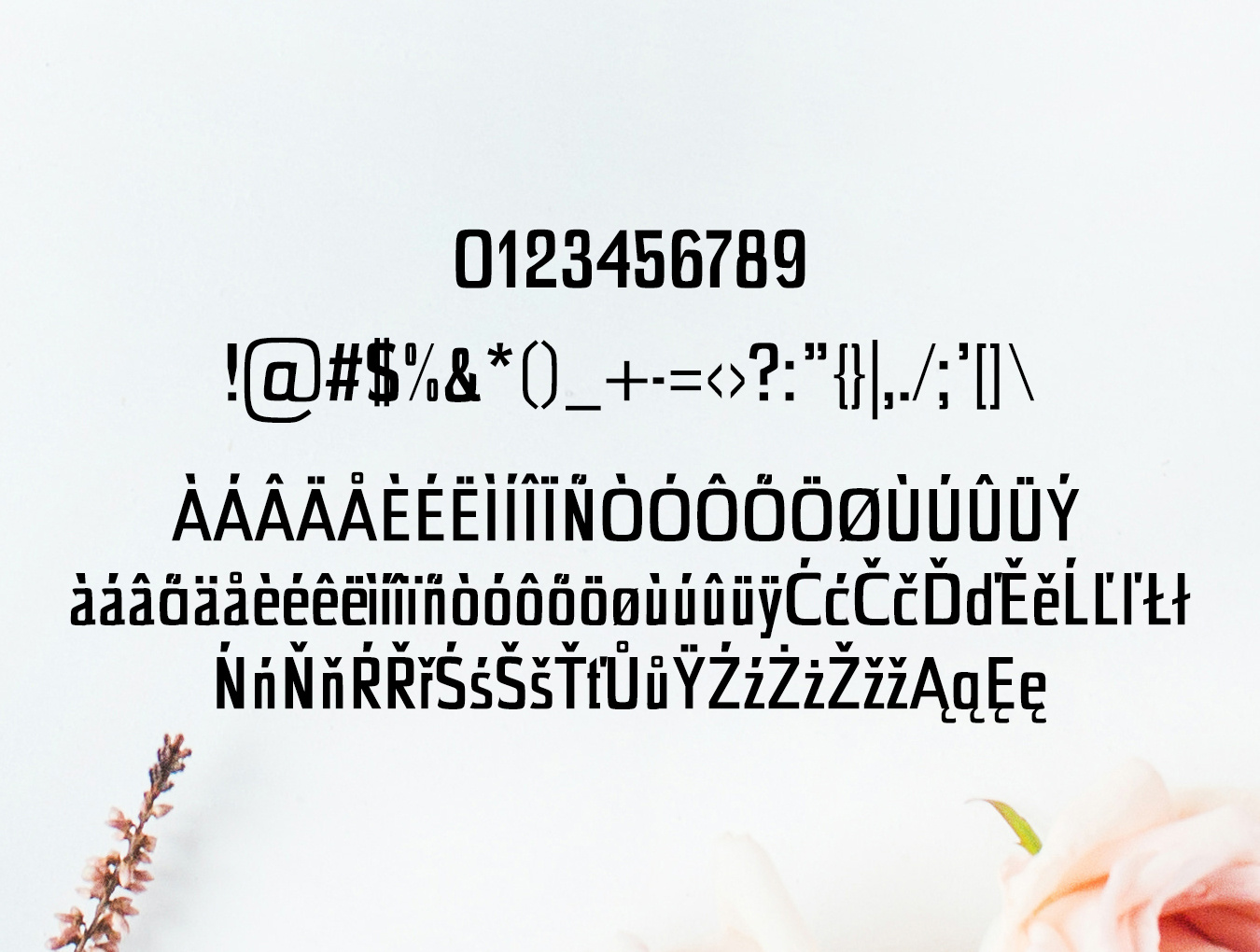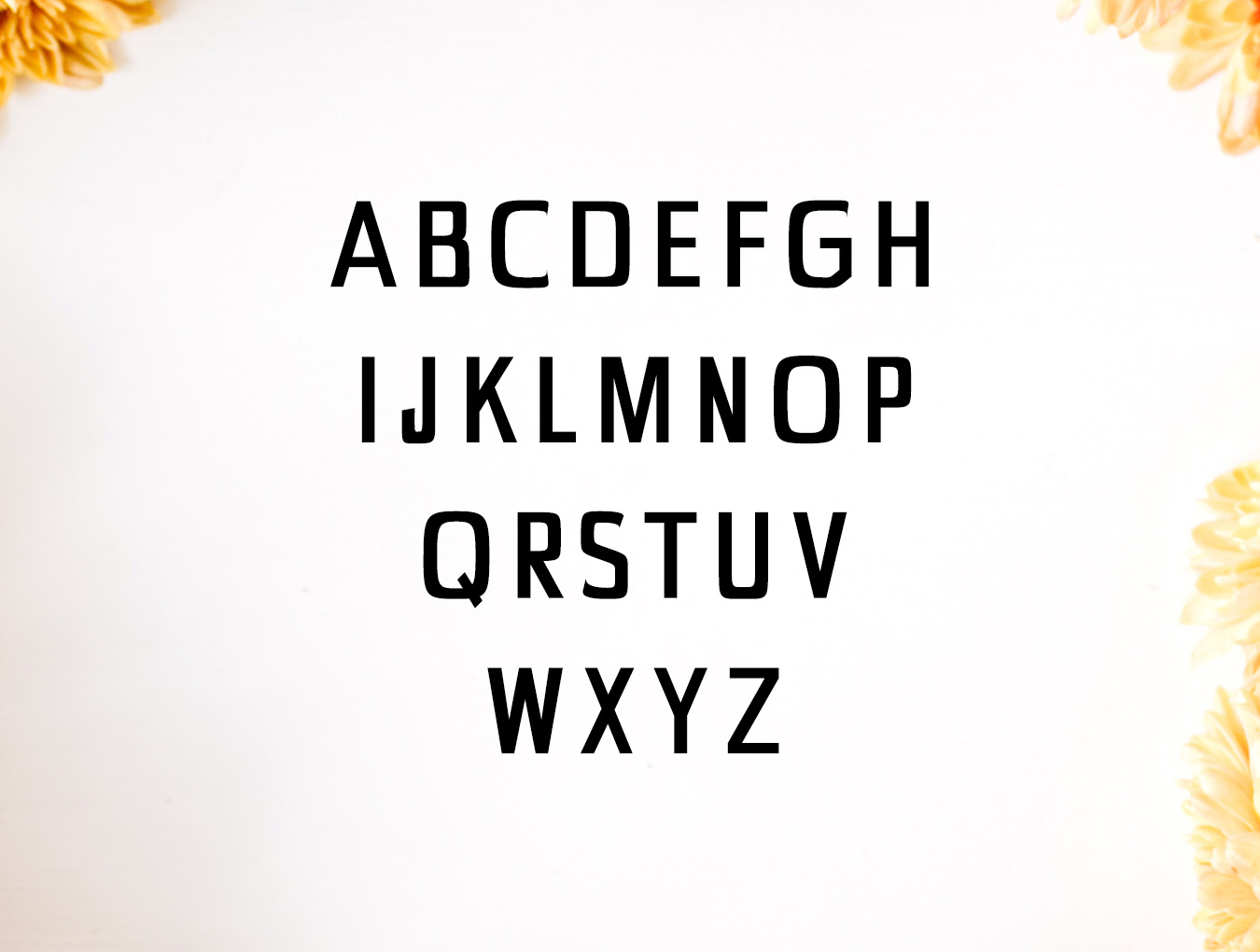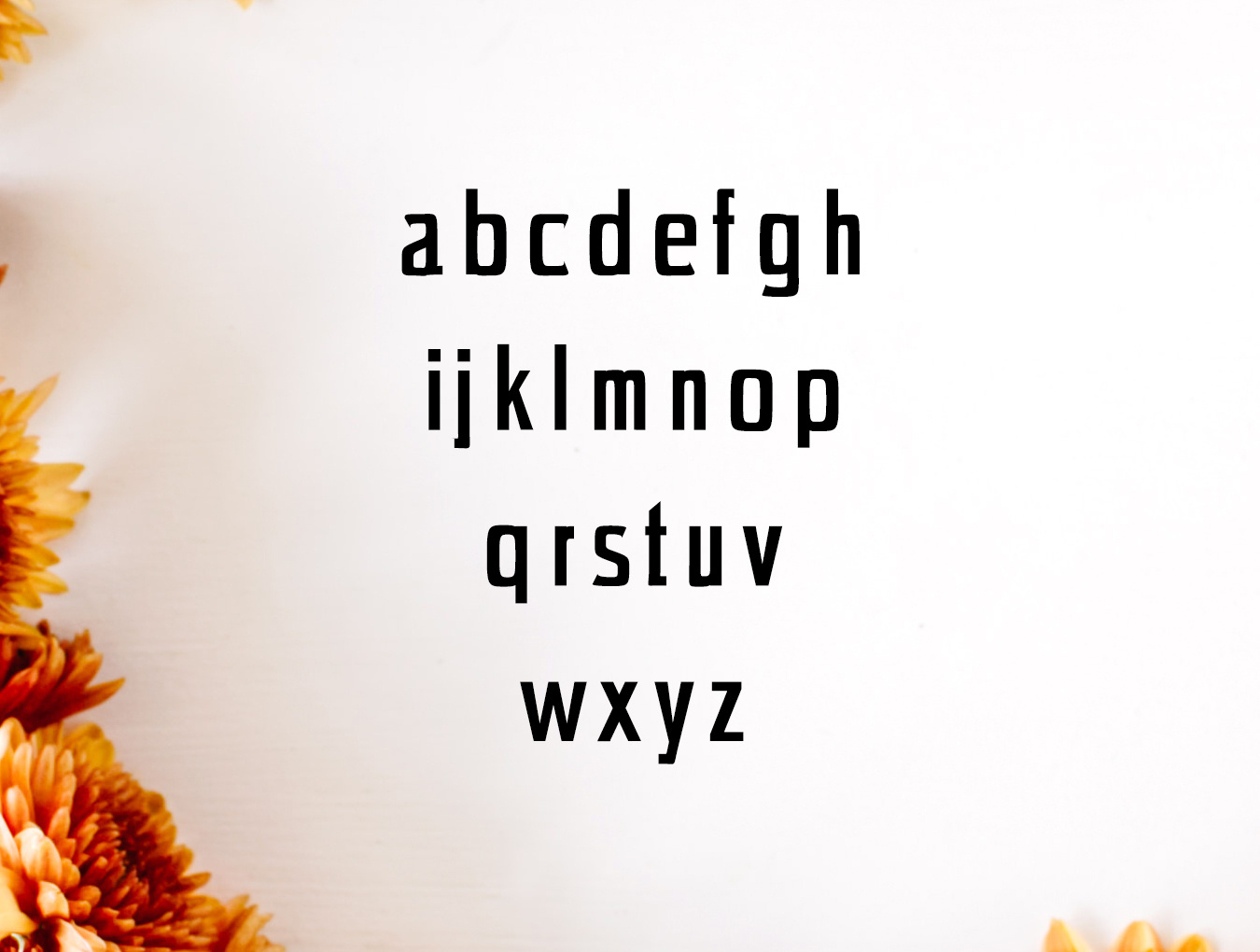
Chrys Sans Serif 4字体家庭装,Chrys Sans Serif字体
Chrys Sans Serif 4 Font Family Pack, Chrys Sans Serif Typeface
Chrys Sans Serif Typeface是一款最小的干净无衬线字体系列,包含4个砝码,具有独特而现代的无衬线外观和感觉。非常适合华丽的徽标,标题,网页布局和品牌。如果你想尝试一个优雅的外观,它看起来华丽,所有帽子都有宽大的间距,或者在大写字母和小写字母中完美无瑕。